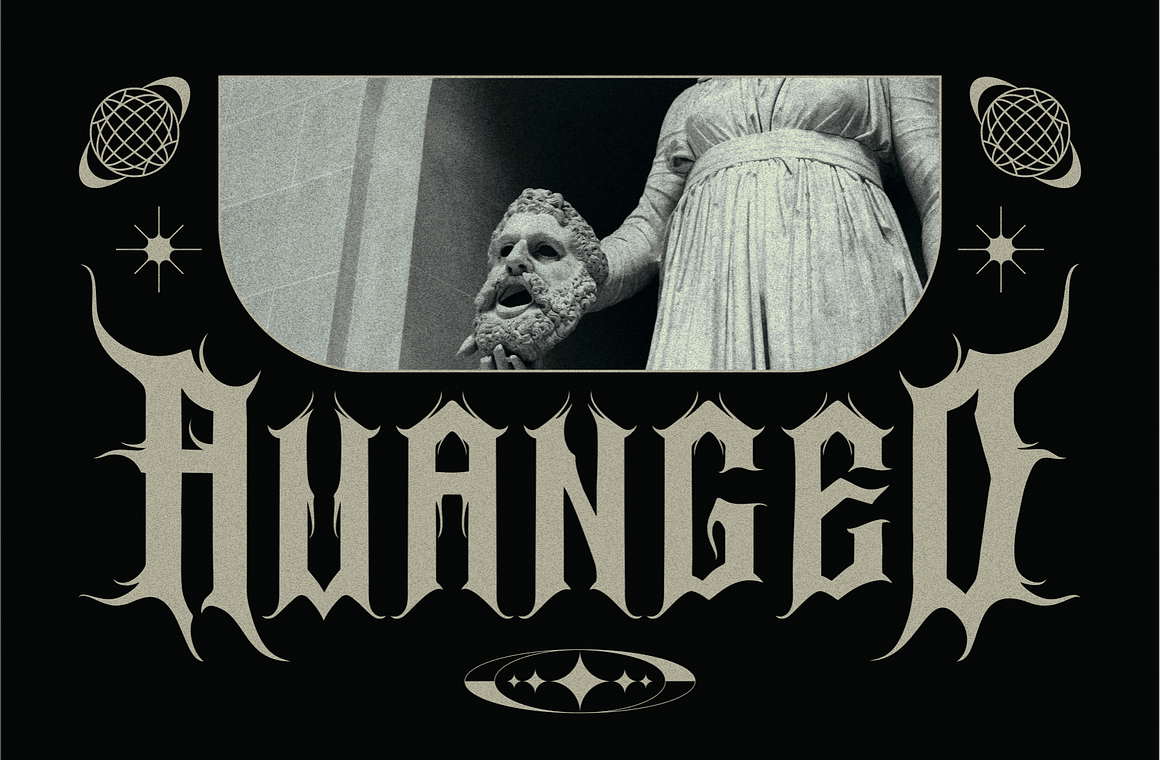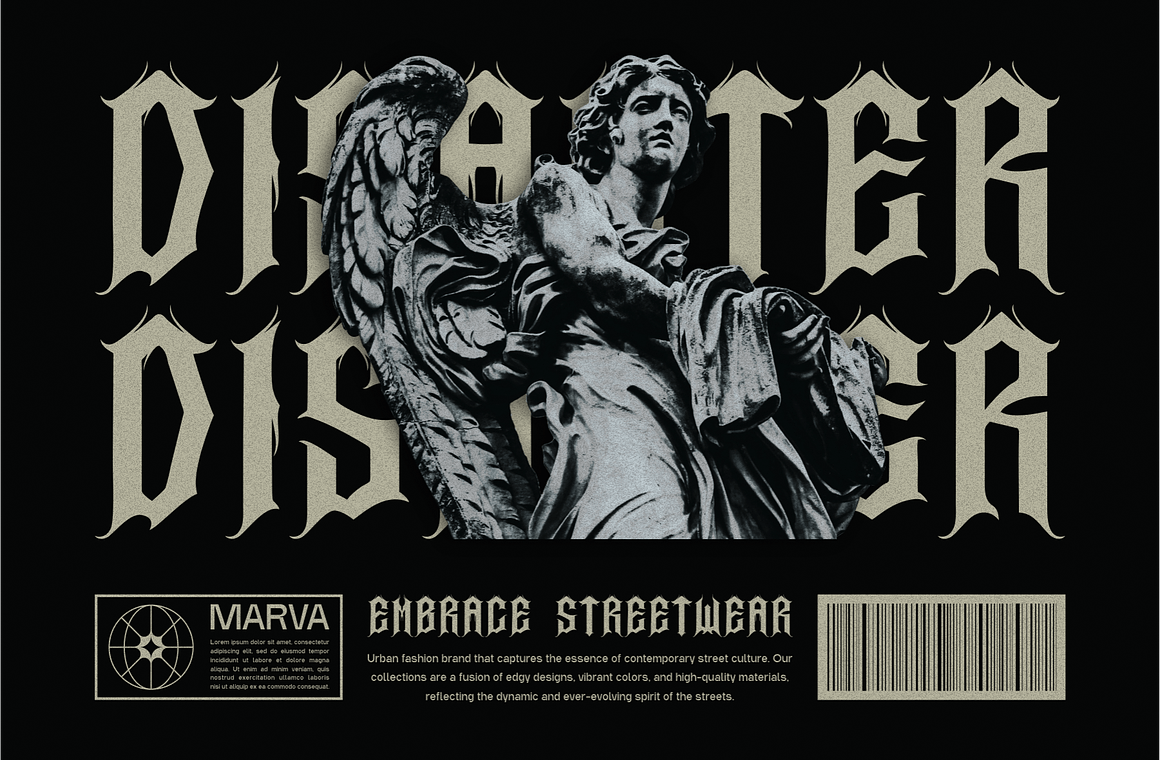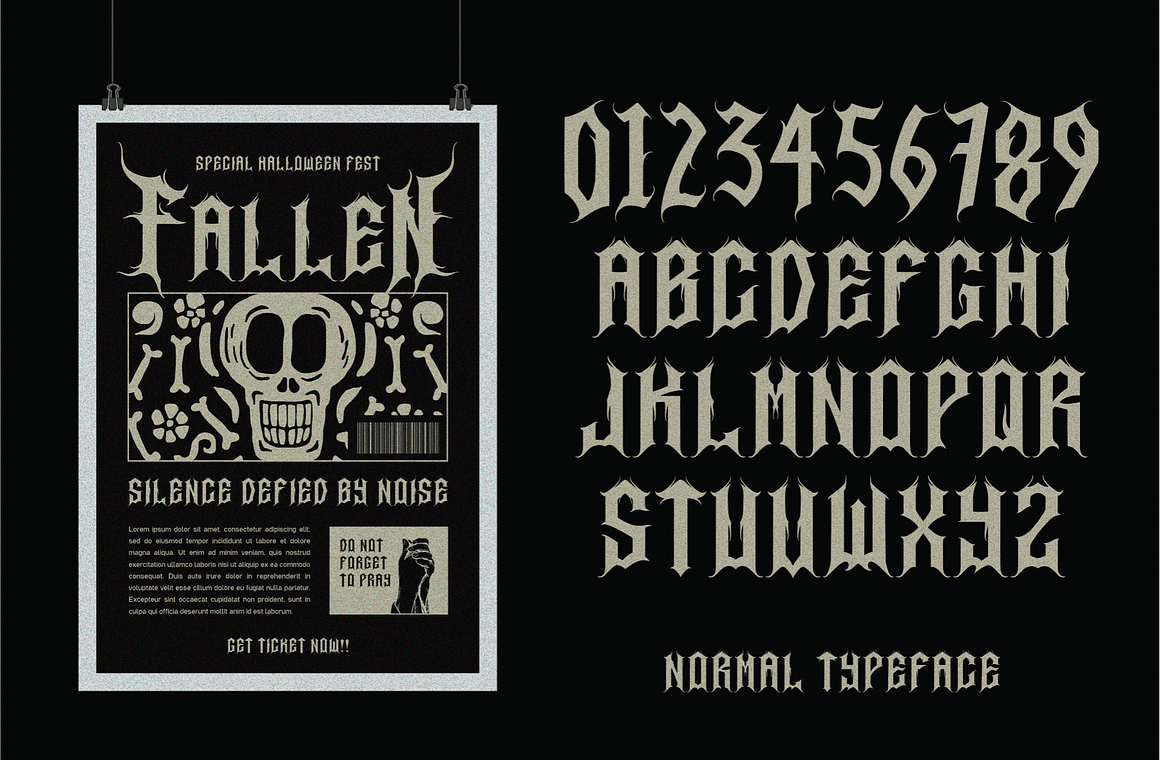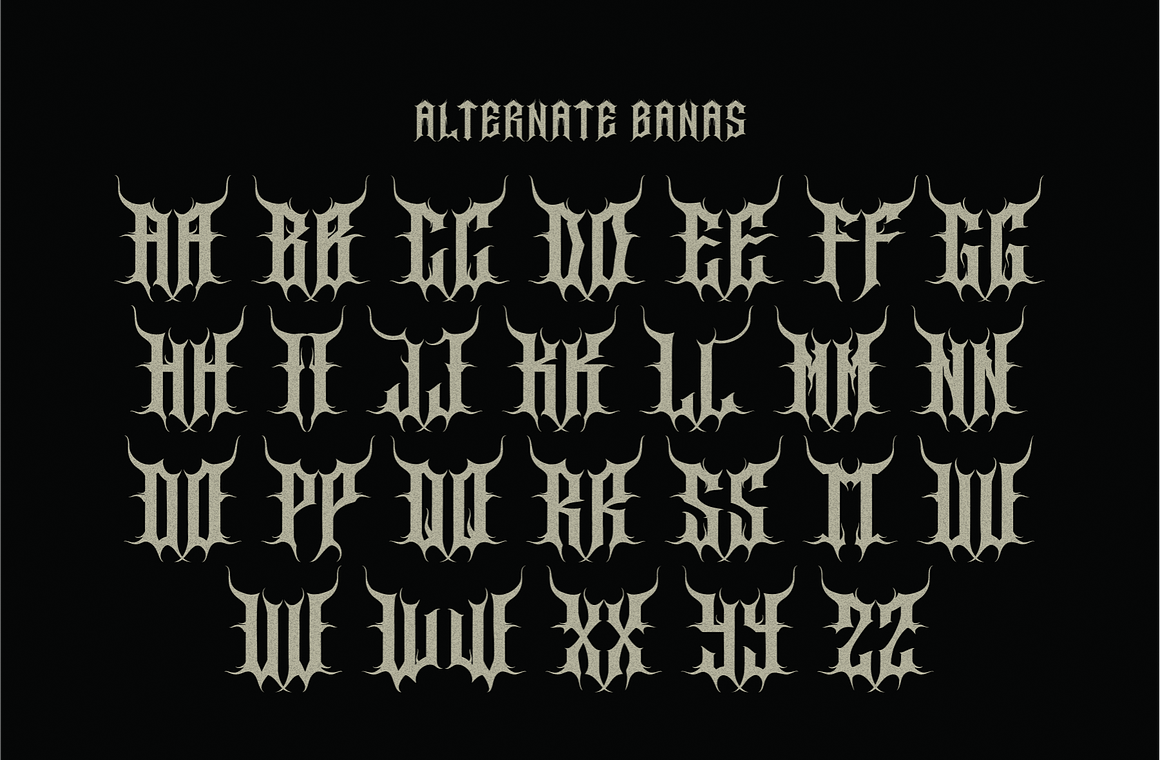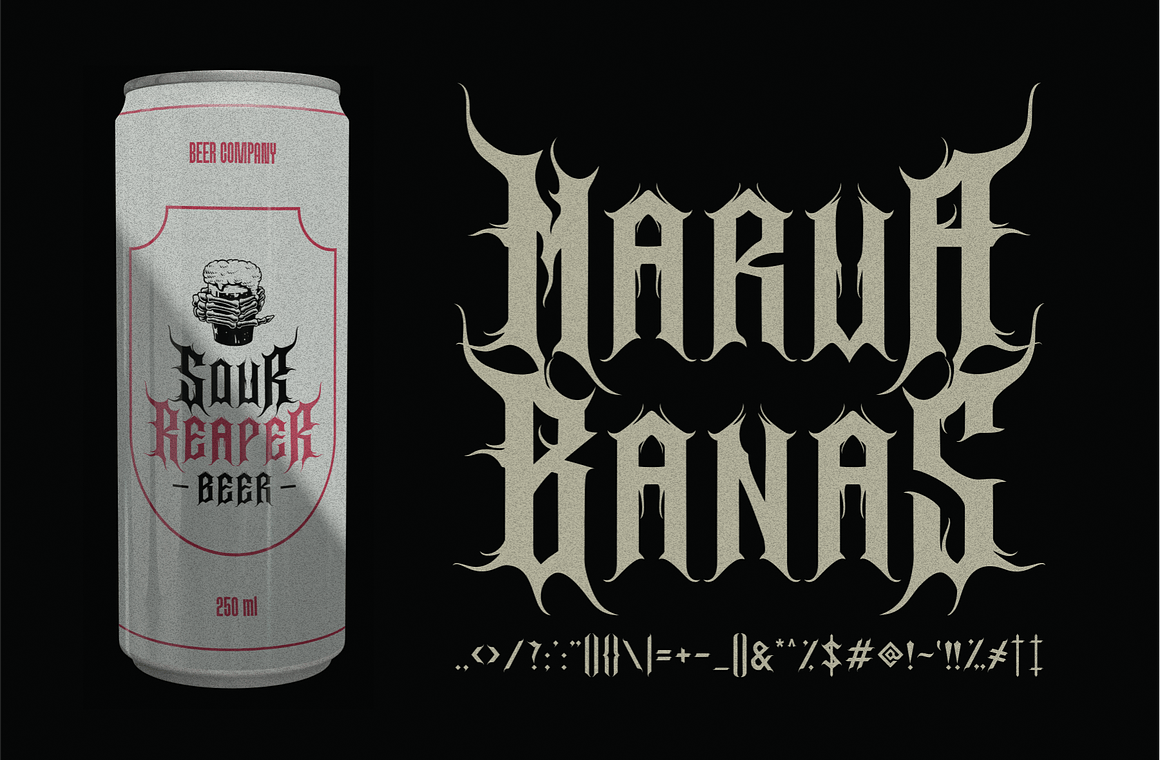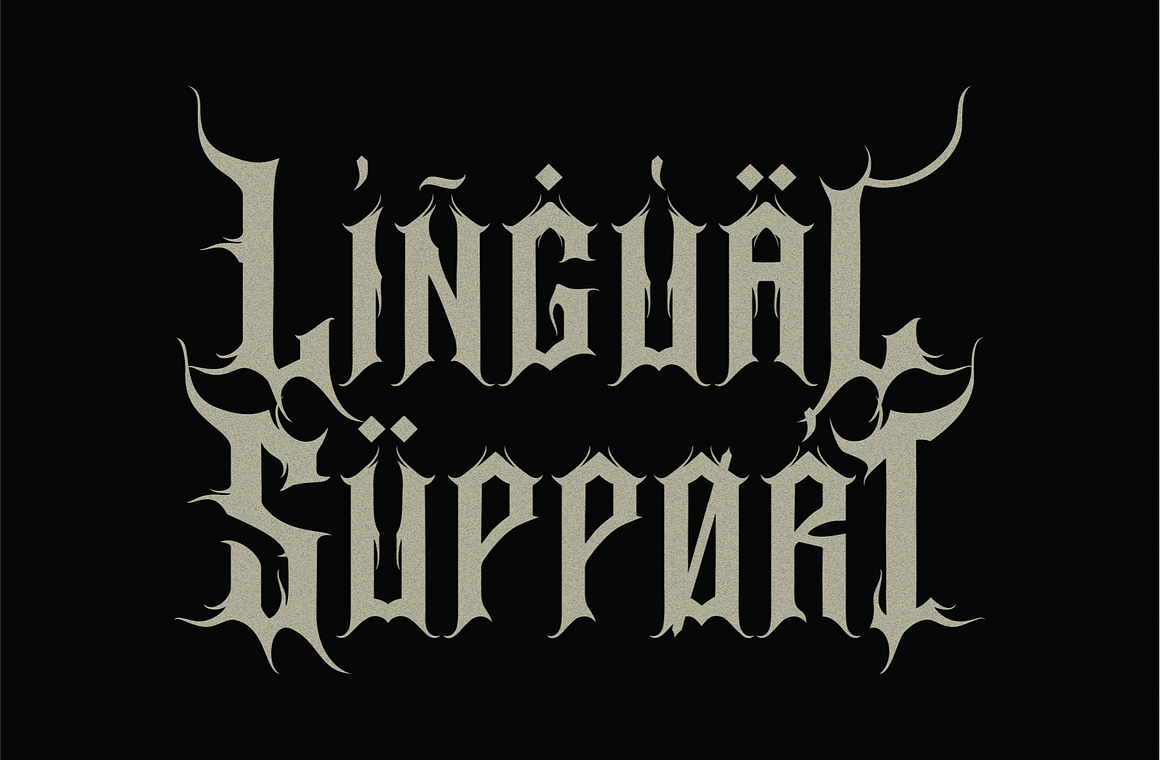
Banas là một phông chữ metal bắt nguồn từ từ “Banaspati,” một ác quỷ trong thần thoại Indonesia. Phông chữ này tượng trưng cho những nét bút của lửa, gợi nhớ đến Banaspati, thường được mô tả như một thực thể rực lửa đáng sợ.
Banas mang phong cách Trang trí Gothic, tạo nên vẻ u ám và mạnh mẽ. Mỗi chữ cái trong phông chữ này được thiết kế với những chi tiết tinh xảo giống như ngọn lửa bùng cháy, tạo nên một diện mạo kịch tính và tràn đầy năng lượng. Ngoài ra, phông chữ còn bao gồm một số biến thể cho các chữ hoa, mang lại sự linh hoạt và đa dạng trong cách ứng dụng.
Với sự kết hợp giữa yếu tố gothic và trang trí, Banas là lựa chọn hoàn hảo cho những thiết kế cần chút rùng rợn, bí ẩn và mãnh liệt. Nó lý tưởng cho logo các ban nhạc metal, poster buổi hòa nhạc, bìa album, áo thun và nhiều dự án sáng tạo khác muốn làm nổi bật thẩm mỹ u tối và rực cháy.